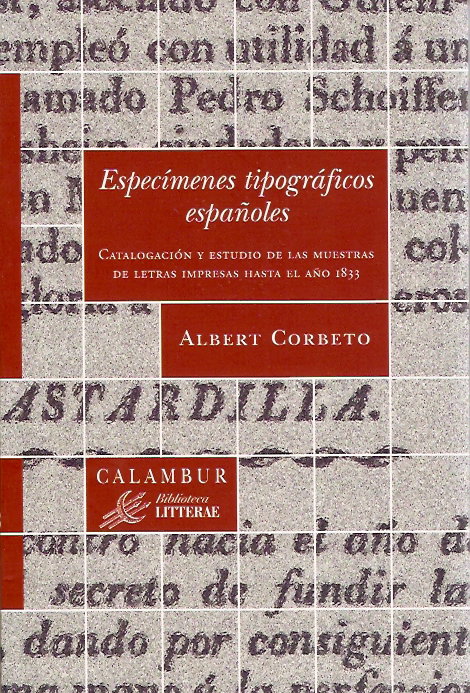
No podíamos despedir el 2010 con una mejor noticia. Acaba de publicarse por la Editorial Calambur el libro de Albert Corbeto, Especímenes tipográficos españoles. Catalogación y estudio de las muestras de letras impresas hasta el año 1833.
Todos aquellos que nos interesamos por la historia de la tipografía en España, siempre nos habíamos quejado de la escasez de bibliografía acerca de uno de los productos fundamentales de la imprenta y que son imprescindibles para su estudio como son los muestrarios de letras.
Aparte de los propios catálogos, toda la documentación disponible acerca de encargos, transacciones comerciales, etc que podían conformar el contexto ideal para conocer mejor el desarrollo de la creación tipográfica en España estaba diseminada en amplios legajos de diferentes archivos del Estado. Y lo que puede parecer una obra de amplia utilidad pero de difícil concreción ha visto la luz gracias a la convencida apuesta de Emilio Torné y su editorial y al fenomenal trabajo del historiador Albert Corbeto.
Albert Corbeto es historiador del arte y realiza su actividad profesional en la Real Academia de Buenas Letras de Barcelona al mismo tiempo que prepara su tesis doctoral sobre la historia de la imprenta en España. Su interés por la imprenta se ha visto reflejado en sendos estudios sobre la tipografía española del siglo XVIII tanto en su vertiente económica como creativa y en la que ha investigado además la aportación de los grandes calígrafos al desarrollo de una tipografía propia del país.
En definitiva, se trata de una obra fundamental tanto para aquellos que tienen interes en conocer los tipos comercializados en España hasta mediados del siglo XIX desde un punto de vista gráfico como para los que la utilizarán como material de consulta para futuras investigaciones. Podemos afirmar con rotundidad que habrá un antes y un después en la articulación de la historia de la tipografía española marcado por la aparición de este libro.
«Las muestras de letras de imprenta han sido siempre un material de circulación limitada y restringido básicamente a un ámbito profesional. Se trata de aquellos impresos, libros u hojas sueltas, que contienen ejemplos de los caracteres que un grabador o fundidor, o un impresor, anuncian en vistas a una transacción comercial determinada. A finales del siglo XIX, los precursores en el estudio de la historia de los caracteres de imprenta consideraron la utilidad que las muestras de letras podían tener en el conocimiento del material tipográfico y de la imprenta en general y, al mismo tiempo, iniciaron la tendencia coleccionista que permitió preservar muchos de los ejemplares que se conservan en la actualidad. La relevancia concedida a estos impresos supuso una influencia decisiva en los métodos de las nuevas generaciones de investigadores y estimuló la aparición de numerosas aportaciones posteriores que facilitaron la localización y reproducción de muchas de las muestras y, gracias a ello, un más profundo conocimiento del origen y circulación de los diversos diseños de letras.
Este impulso no se vio reflejado en los estudios históricos del libro español y hasta ahora no se había realizado ningún esfuerzo por estudiar y catalogar de forma sistemática los especímenes tipográficos impresos en España. El trabajo que aquí se presenta subsana esta carencia y ofrece un panorama de la producción y comercio de tipos en el período de la imprenta manual, a la vez que proporciona una útil herramienta de trabajo para que futuras investigaciones puedan continuar con la reconstrucción de la todavía desconocida historia de la tipografía española.»